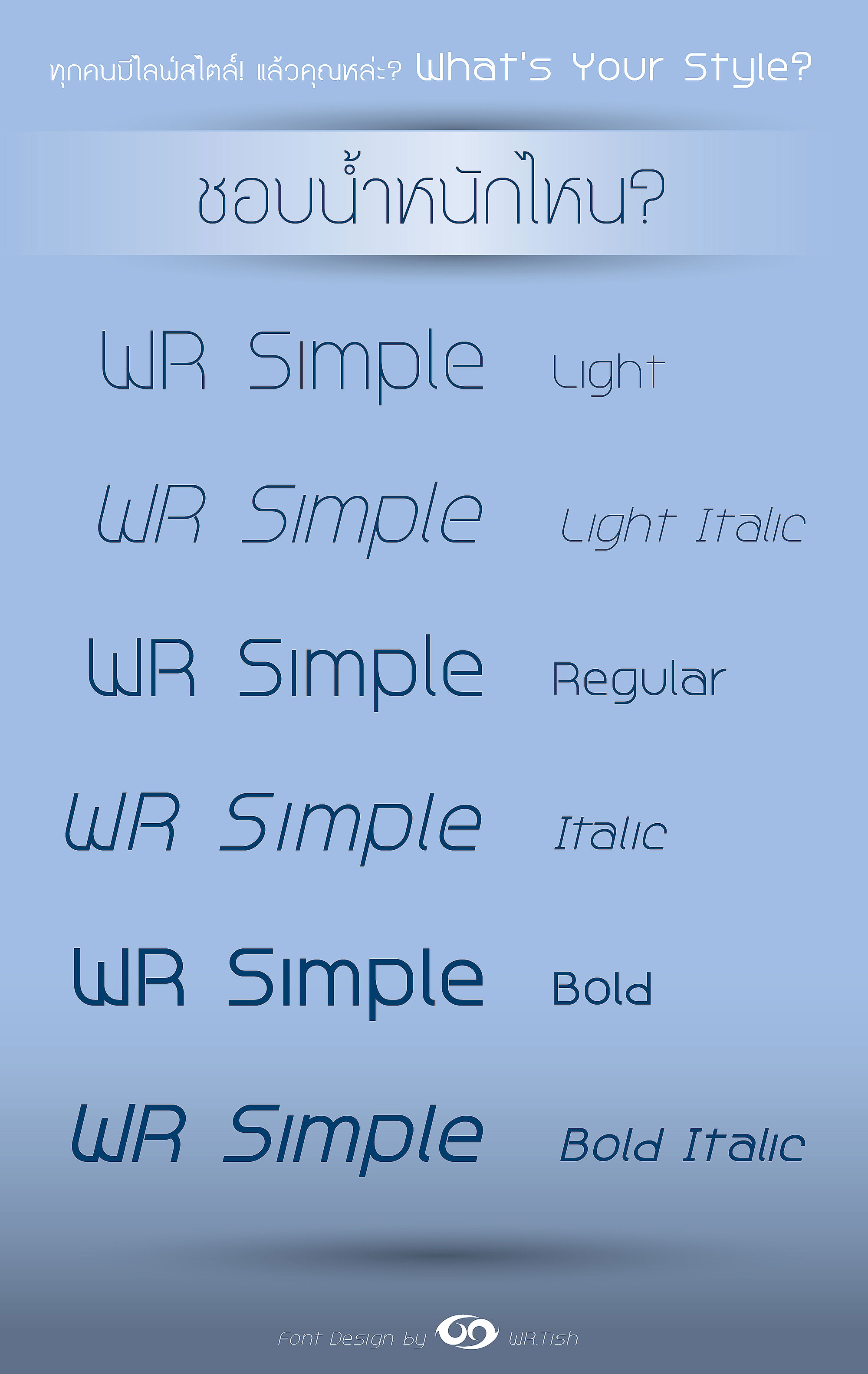
ขออนุมัติปล่อยฟอนต์ WR Simple ค่ะ
ฟอนต์นี้ไม่รู้ได้แรงบันดาลใจจากไหน! รู้แต่ว่าอยากได้ฟอนต์เรียบๆ มาใช้สักตัวหนึ่ง แต่พอทำเสร็จไหงไปละม้ายคล้ายฟอนต์ท่านอื่นได้  :18: (คงเพราะซึมซับไปโดยไม่รู้ตัว) การทำฟอนต์นี้สอนให้รู้ว่าผู้จัดทำนั้นต้องมีความมานะอุตสาหะเป็นอย่างมากกกกกก หากใครไม่เคยทำน่าจะลองดูสักครั้งในชีวิต
แปะภาพน้ำหนักของฟอนต์ Simple มาให้แล้วนะคะ